นิวยอร์กแยงกี้ฟอนต์
เผยแพร่แล้ว: 2023-05-09New York Yankees เป็นหนึ่งในทีมเบสบอลที่โดดเด่นที่สุดในประวัติศาสตร์ ด้วยเรื่องราวในอดีตอันเข้มข้น ทีมได้ผ่านการเปลี่ยนแปลงมากมายในช่วงหลายปีที่ผ่านมา แต่สิ่งหนึ่งที่ไม่เปลี่ยนแปลงคือแบบอักษรของโลโก้
การออกแบบตัวอักษรมีบทบาทสำคัญในการสร้างแบรนด์ และแบบอักษรของโลโก้ New York Yankees ก็ไม่มีข้อยกเว้น
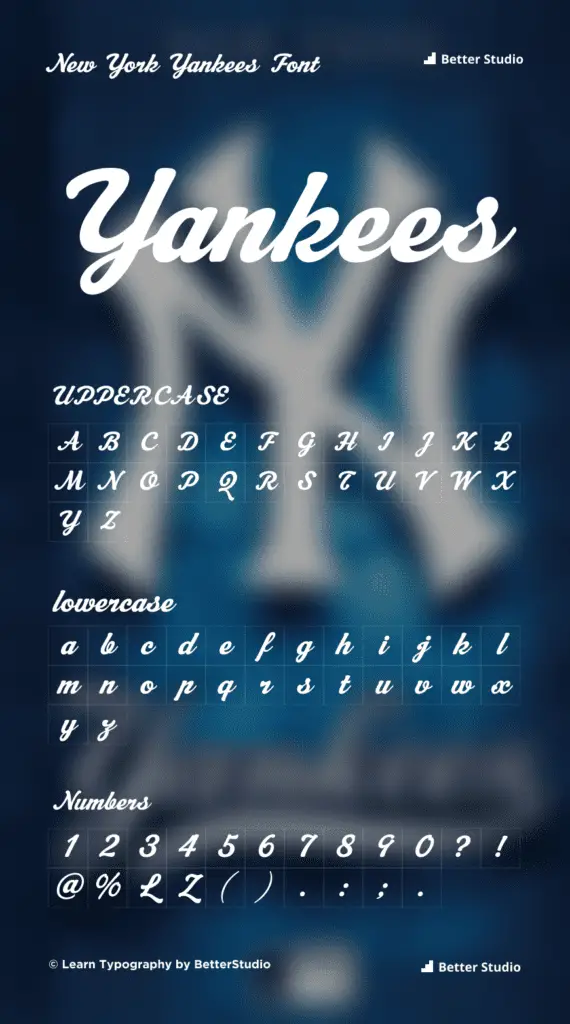
ชื่อแบบอักษรของโลโก้ The New York Yankees คืออะไร?
แบบอักษรที่ใช้ในโลโก้ของ New York Yankees เรียกว่า "Machiarge and Jersey M54" ซึ่งเป็นแบบอักษรที่ใกล้เคียงที่สุดกับแบบโลโก้ดั้งเดิม อย่างไรก็ตาม มีแบบอักษรอื่นๆ ที่คล้ายกับแบบอักษรนี้ เช่น Avenir Black และ Oswald Medium
ฟอนต์ที่ใช้สำหรับโลโก้คือ Machiarge และหมายเลขที่ด้านหลังของเสื้อใช้ฟอนต์ Jersey M54
ทางเลือกและสไตล์ที่คล้ายกันกับ Machiarge และ Jersey M54
หากคุณต้องการใช้ฟอนต์อื่นที่มีการออกแบบและการใช้งานคล้ายกับฟอนต์ New York Yankees มีตัวเลือกอื่นให้เลือกมากมาย นี่คือรายการแบบอักษรสำรอง 5 แบบที่คุณสามารถใช้ได้:
- ตัวอักษรสีดำ Avenir
- แบบอักษร Hind Madurai
- ออสวอลด์ ฟอนต์ขนาดกลาง
- ตัวอักษร League Gothic
- ฟอนต์ Bebas Neue
นักออกแบบคนไหนสร้างแบบอักษร New York Yankees?
แบบอักษร Machiarge และ Jersey M54 ซึ่งใช้ในโลโก้ New York Yankees สร้างขึ้นโดย Justme54s และ Ryoichi Tsunekawa
Justme54s เป็นนักออกแบบในสหราชอาณาจักรที่เชี่ยวชาญด้านการสร้างฟอนต์ที่ได้รับแรงบันดาลใจจากป้ายและโฆษณาสไตล์วินเทจของอเมริกา
Ryoichi Tsunekawa เป็นนักออกแบบแบบอักษรชาวญี่ปุ่นและเป็นผู้ก่อตั้งโรงหล่อแบบอักษรอิสระที่ชื่อว่า Dharma Type นักออกแบบทั้งสองได้สร้างฟอนต์ยอดนิยมอื่นๆ อีกมากมายที่ใช้กันอย่างแพร่หลายในการสร้างแบรนด์ โฆษณา และสื่อสิ่งพิมพ์
นี่คือข้อมูลเกี่ยวกับนิวยอร์กแยงกี้
New York Yankees เป็นทีมเบสบอลมืออาชีพที่ตั้งอยู่ในเขตบรองซ์ของนิวยอร์กซิตี้ พวกเขาก่อตั้งขึ้นในปี 2444 ในชื่อ Baltimore Orioles และย้ายไปนิวยอร์กในปี 2446
ตั้งแต่นั้นเป็นต้นมา พวกเขาได้กลายเป็นหนึ่งในทีมกีฬาที่ประสบความสำเร็จและมีชื่อเสียงมากที่สุดในโลก คว้าแชมป์ World Series ถึง 27 รายการ และสร้างผู้เล่นระดับตำนานนับไม่ถ้วน เช่น Babe Ruth, Lou Gehrig, Joe DiMaggio และ Derek Jeter
โลโก้ New York Yankees ซึ่งมีชื่อย่อของทีมว่า “NY” ในฟอนต์ serif แบบคลาสสิก ได้กลายเป็นสัญลักษณ์ที่จดจำได้ในทันทีของทีมและเมือง
แบบอักษร Machiarge และ Jersey M54 ได้รับเลือกเนื่องจากรูปลักษณ์ที่ดูโดดเด่น แข็งแกร่ง และแข็งแรง ซึ่งสะท้อนถึงจิตวิญญาณของทีมและแฟนๆ ได้อย่างสมบูรณ์แบบ ตั้งแต่นั้นมาได้กลายเป็นส่วนสำคัญของการสร้างแบรนด์และสินค้าของทีม โดยปรากฏบนเสื้อและหมวก ไปจนถึงของที่ระลึกและเอกสารทางการตลาด
โดยรวมแล้ว แบบอักษรของโลโก้ New York Yankees เป็นเครื่องพิสูจน์ถึงมรดกที่ยั่งยืนและความนิยมของทีม ตลอดจนพลังของการพิมพ์ในการสร้างแบรนด์ที่มีประสิทธิภาพและน่าจดจำ
โดยสรุป แบบอักษรของโลโก้ New York Yankees สร้างขึ้นโดย Justme54s และ Ryoichi Tsunekawa เป็นแบบอักษรที่โดดเด่นและเป็นตัวหนาที่รวบรวมจิตวิญญาณของทีมกีฬาที่ประสบความสำเร็จมากที่สุดทีมหนึ่งในประวัติศาสตร์ได้อย่างสมบูรณ์แบบ